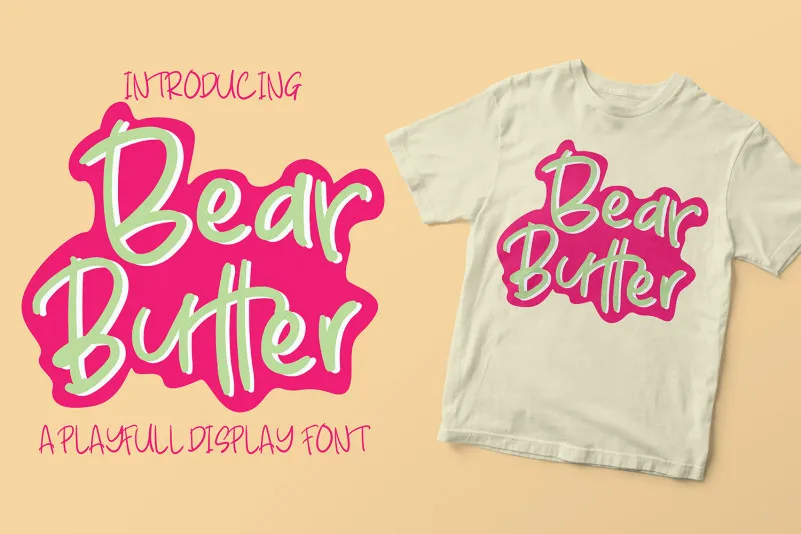
A ‘Bear Butter Font’ é uma opção divertida e prática para designers que desejam dar ao seu projeto uma cara descontraída e alegre. Seus traços leves e simpáticos são perfeitos para adicionar um toque irreverente em variados tipos de projetos, seja eletrônico ou impresso. Especificamente ideal para aplicativos gráficos como logotipos, selos, ilustrações e embalagens. Esta fonte Display é uma escolha versátil que certamente adicionará um brilho ao seu trabalho. Seja você criando material para a web, para o jornal ou até mesmo para camisetas customizadas – a ‘Bear Butter Font’ está sempre pronta para dar aquele toque especial à sua próxima criação visual.